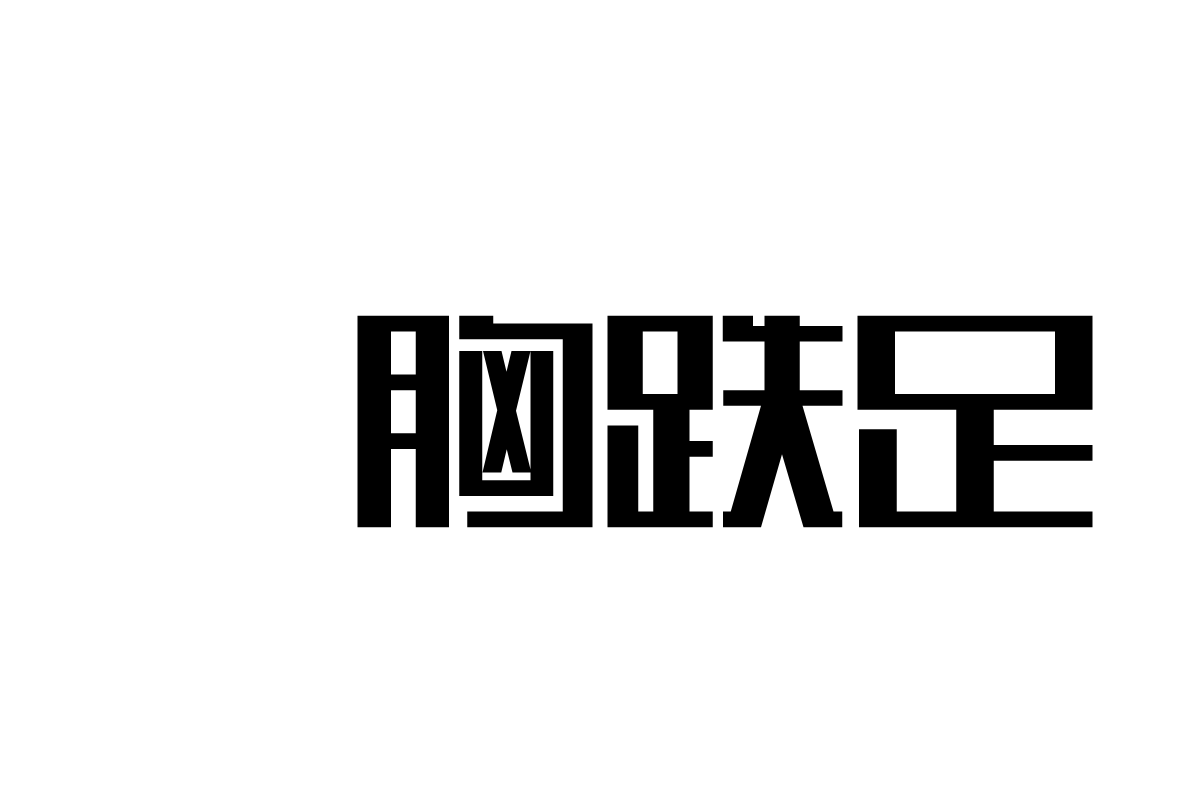
汉仪刚艺体-75是一款具有现代感和艺术气息的字体,适用于各种设计领域。这款字体采用了简洁而有力的笔触,线条流畅且有力,给人一种强烈的视觉冲击力。它的字形结构紧凑,笔画粗细适中,既适合用于标题、广告等需要突出文字的场合,也适合用于正文、说明文等需要清晰表达内容的场合。
汉仪刚艺体-75的特点在于其独特的风格和表现力,使得它在众多字体中脱颖而出。它的线条流畅且有力,给人一种强烈的视觉冲击力;同时,它的字形结构紧凑,笔画粗细适中,既适合用于标题、广告等需要突出文字的场合,也适合用于正文、说明文等需要清晰表达内容的场合。
总的来说,汉仪刚艺体-75是一款非常适合现代设计需求的字体,无论是在品牌宣传、广告设计还是其他各类设计项目中,都能发挥出良好的效果。